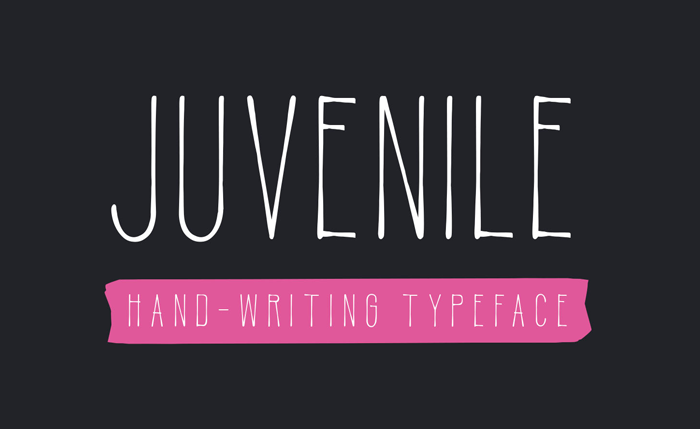
Bem-vindo a mais uma oferta de fontes sans serif da nossa biblioteca! Hoje, apresentamos Juvenile Typeface, criado pelo designer Hamilton para ilustrar as qualidades amigáveis e alegres que essa fonte oferece aos projetos digitais. Juvenile é um tipo grotesco, desenhado à mão livre. Ideal tanto para logotipos quanto para trabalhos web ou aplicativos de blogue, também se destaca em design para revistas, livros e embalagens de produtos. Suas linhas leves e delicadas trazem uma sensação acolhedora aos textos, tornando-a perfeita para qualquer tipo de uso. Já imaginou sua próxima campanha publicitária cheia de vida com essa fonte? Ou talvez você queira dar um toque divertido às suas fotos postadas nas redes sociais. Não importa o formato ou a plataforma: Juvenile Typeface tem seu lugar em qualquer projeto gráfico, tornando-o uma escolha ótima para qualquer tipo de texto e layout.